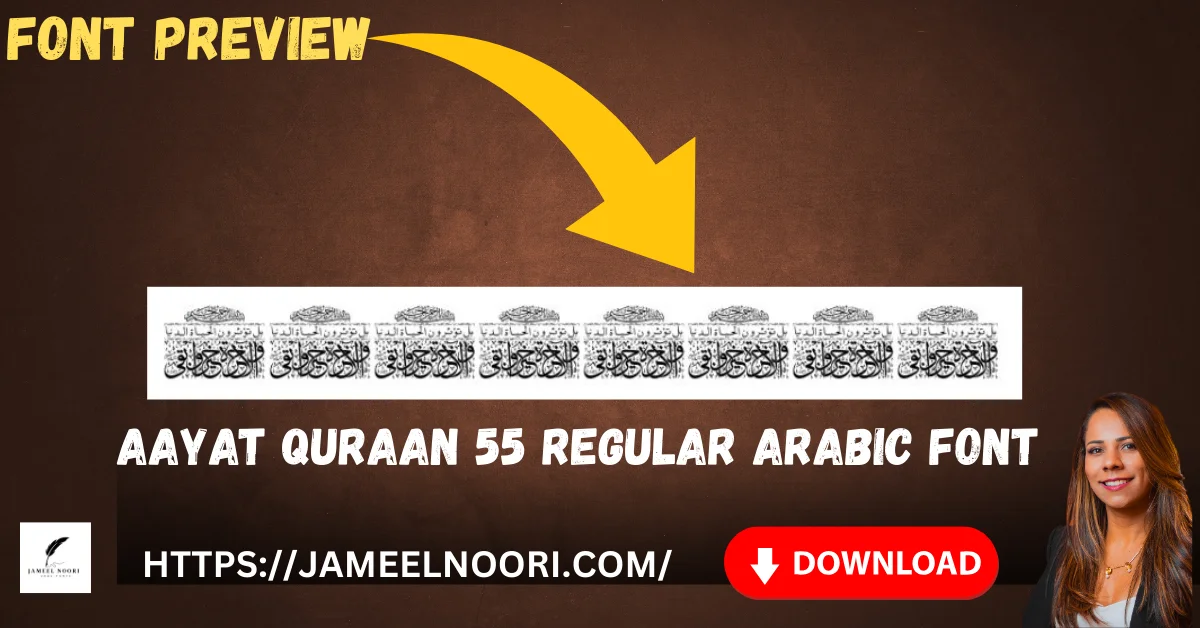
Introduction to Aayat Quraan 55 Regular Arabic Font
Aayat Quraan 55 Regular Arabic Font aik bohot mashhoor aur widely-used Arabic calligraphy font hai jo specially Quranic text aur Islamic designs ke liye perfect mana jata hai. Is font ki beauty, readability aur smooth curves usay designers aur Urdu/Arabic font lovers ke liye behtareen choice banati hain.
Latest Features of Aayat Quraan 55 Regular Arabic Font (Expert Choice)
Aayat Quraan 55 Regular Arabic Font ke features usay unique banate hain. Is font ka style elegant aur readable dono hai. Neeche kuch top features list kiye gaye hain:
- Smooth Arabic calligraphy strokes – professional and elegant look
- Islamic text designs ke liye perfect – specially designed for Islamic content
Key Features of Aayat Quraan 55 Regular Arabic Font
Elegant Calligraphic Design
is font mein traditional Arabic calligraphy ki jhalak milti hai. yeh arabic fonts ki duniya mein apni alag pehchan rakhta hai. Quranic verses ke liye yeh font best hai.
High Readability
Advanced Arabic Ligatures
arabic text mein ligatures ka support hai jo text ko authentic banata hai.
Premium Stroke Quality
har letter ki stroke quality refined hai jo professional look deti hai.